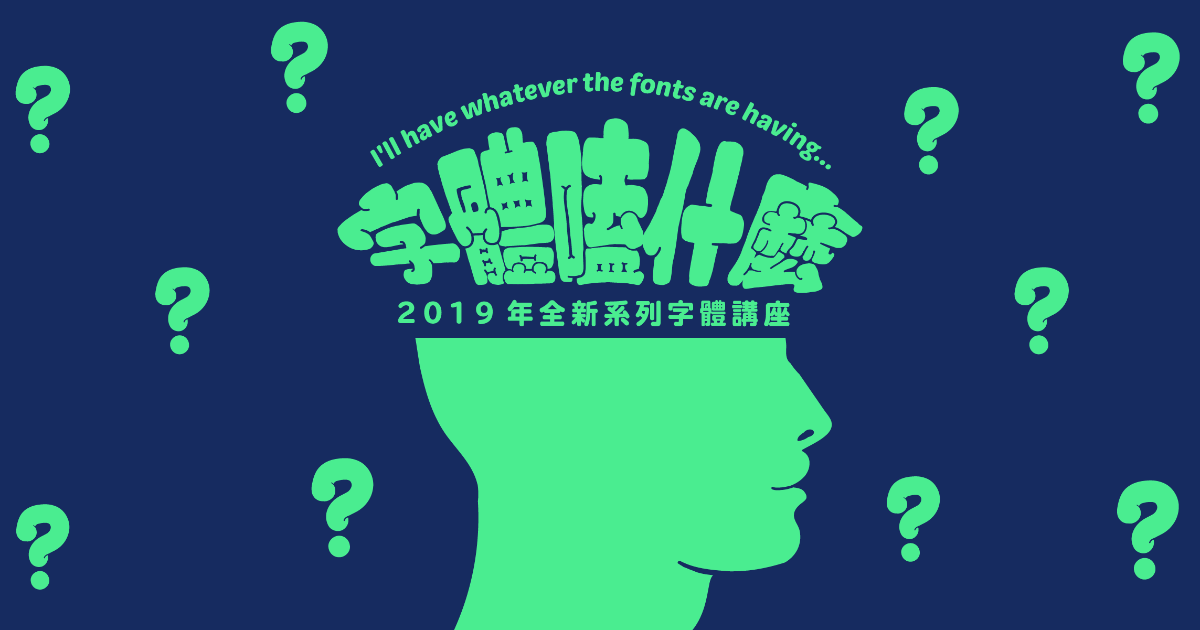
justfont 2019 年全新系列字體講座
🤯字體嗑什麼🤔
—Season 1—
字體嗑⋯⋯巧克力!
不在只用眼力,認識字體也可以靠舌尖。
刺激腦補激素,深度認識巧克力包裝上常見的字體,
並詳細介紹能派上用場的字體關鍵字。
關於字體嗑什麼⋯⋯
根據研究,87%的人都不知道字體隨時都有意見,一見面就默默使喚你的大腦。手機、甜食、啤酒;報表、告示、簡報,都要參一腳。不論你靠什麼吃飯,它都要強勢刷存。這也未免太霸道了!
就算是巧克力也一樣。身為全世界最受歡迎的食物,其實有個難言之隱。總不可能要求老闆貨架上每一款都拆給你試吃看看吧?你與巧克力初次見面的第一印象,其實是由字體決定的。不管是味如嚼蠟超難吃,還是滑順回甘有層次,要價一張伍佰或只要一塊銅板有找,都要找字體幫它自我介紹。
比較貴的巧克力包裝得就比較美嗎?包裝美的巧克力就比較好吃嗎?越好吃的巧克力就一定越貴嗎?越是拆解下去,好像⋯⋯越難歸納出什麼準則。看來,是字體的話術太厲害了。這一次,我們就來聽聽字體的說話之道:
- 黑巧克力(dark chocolate)的口味、定價與包裝的關聯
- 巧克力包裝上常見的字體、符號、數字以及它們的深度分析
- 從字體分析巧克力包裝的風格
- 字體關鍵字:要搜尋我看到的包裝字體,應該要輸入什麼關鍵字?
嘖嘖嘖,像字體這麼控制狂的小東西,千萬別對它一無所知,讓 justfont 說給你聽。不管字體嗑了什麼,都給我來一點!